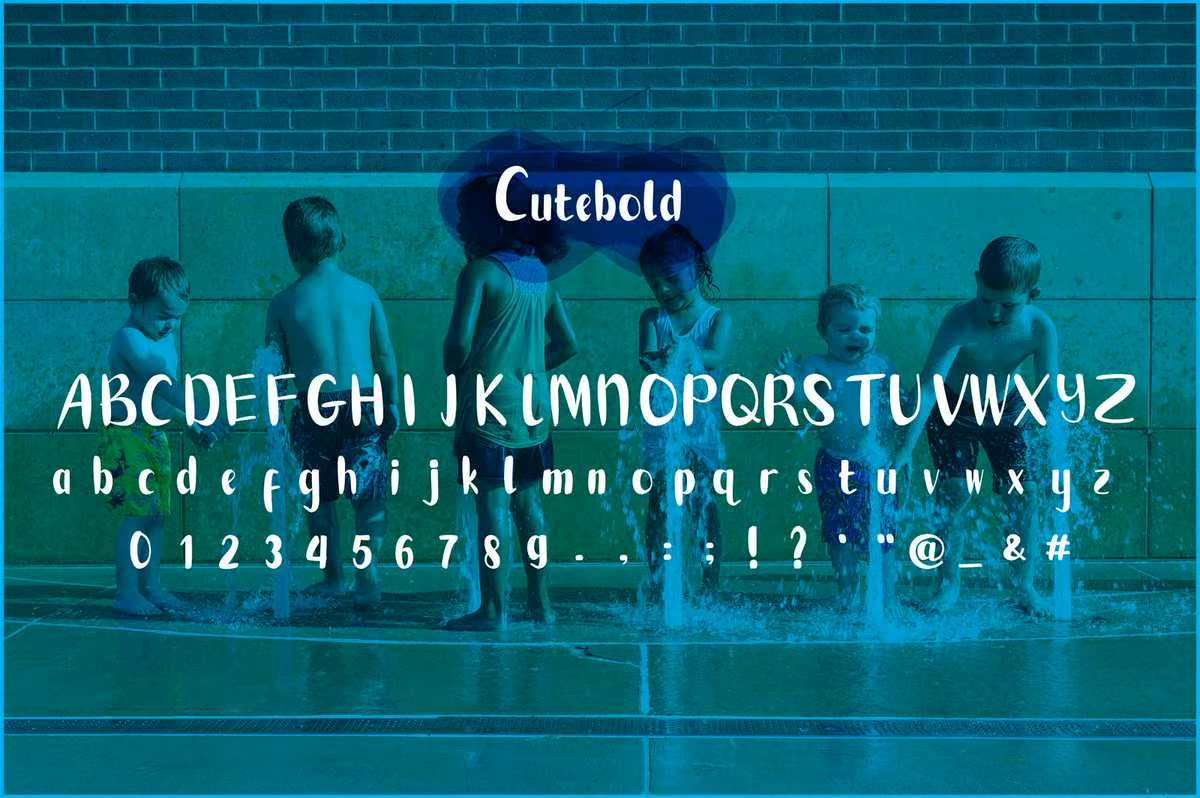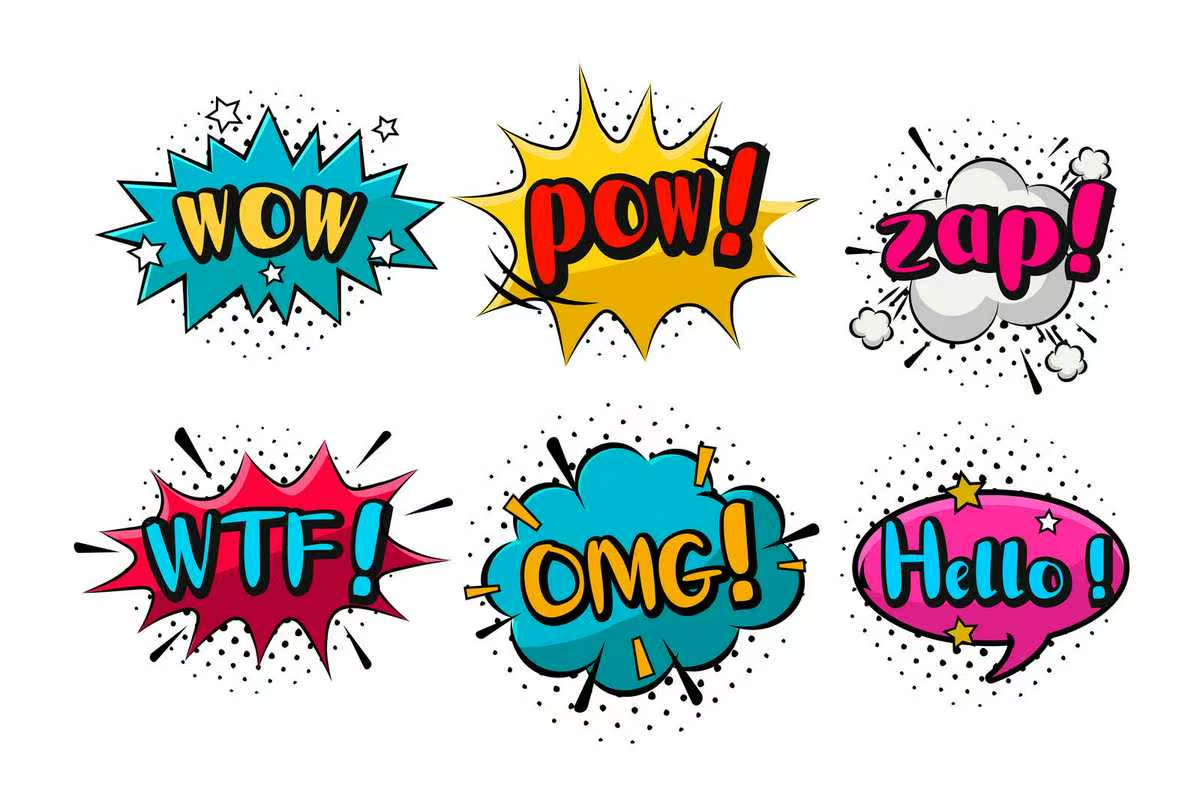
你们好吗?我想很好!介绍,这是我们的第一款产品,我们称之为CuteBoldFont。CuteBoldFont是一款外观更为醒目、曲线更为优美的手机。CuteBoldFont的用途包括:漫画、儿童标志设计产品。下载至AccessAllCarather:点击这里你们好吗?我相信它很好!介绍,这是我们的第一款产品,我们称之为CuteBoldFont。CuteBoldFont是一款字体更大、触感更粗、曲线更优美的产品。CuteBoldFont的用途包括:漫画、婴儿或儿童标志设计产品。下载至访问所有Cara:单击此处